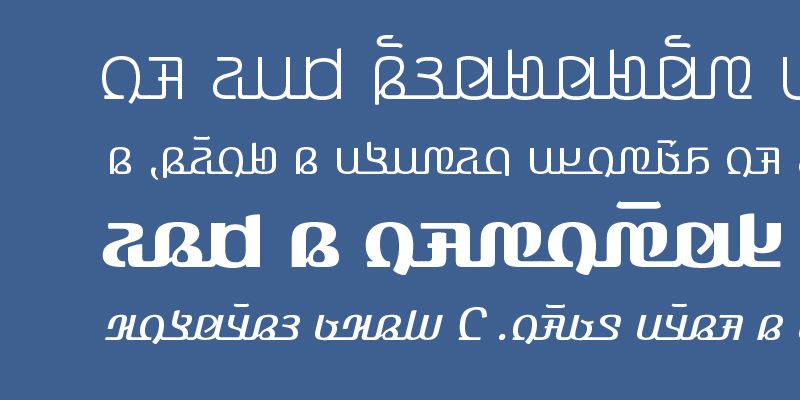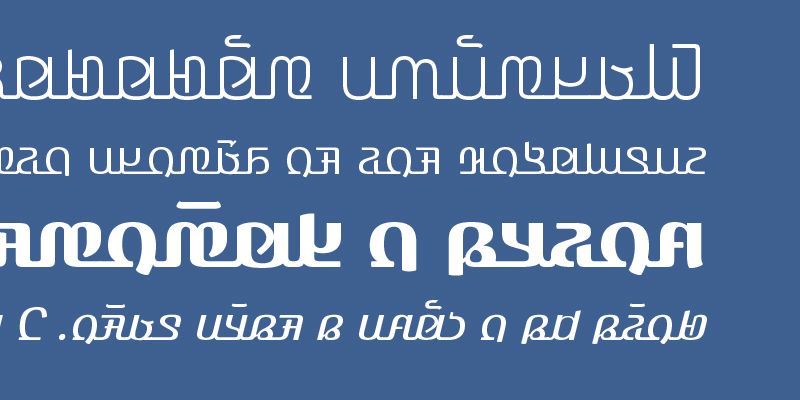
Kigelia Adlam enthält das Zeichensystem der Pular-Sprache, die von den Fulani im subsaharischen Afrika gesprochen wird. Außerdem bietet sie Benutzern einen Stilsatz mit einigen Sonderzeichen sowie Entsprechungen für Basis-Lateinisch.